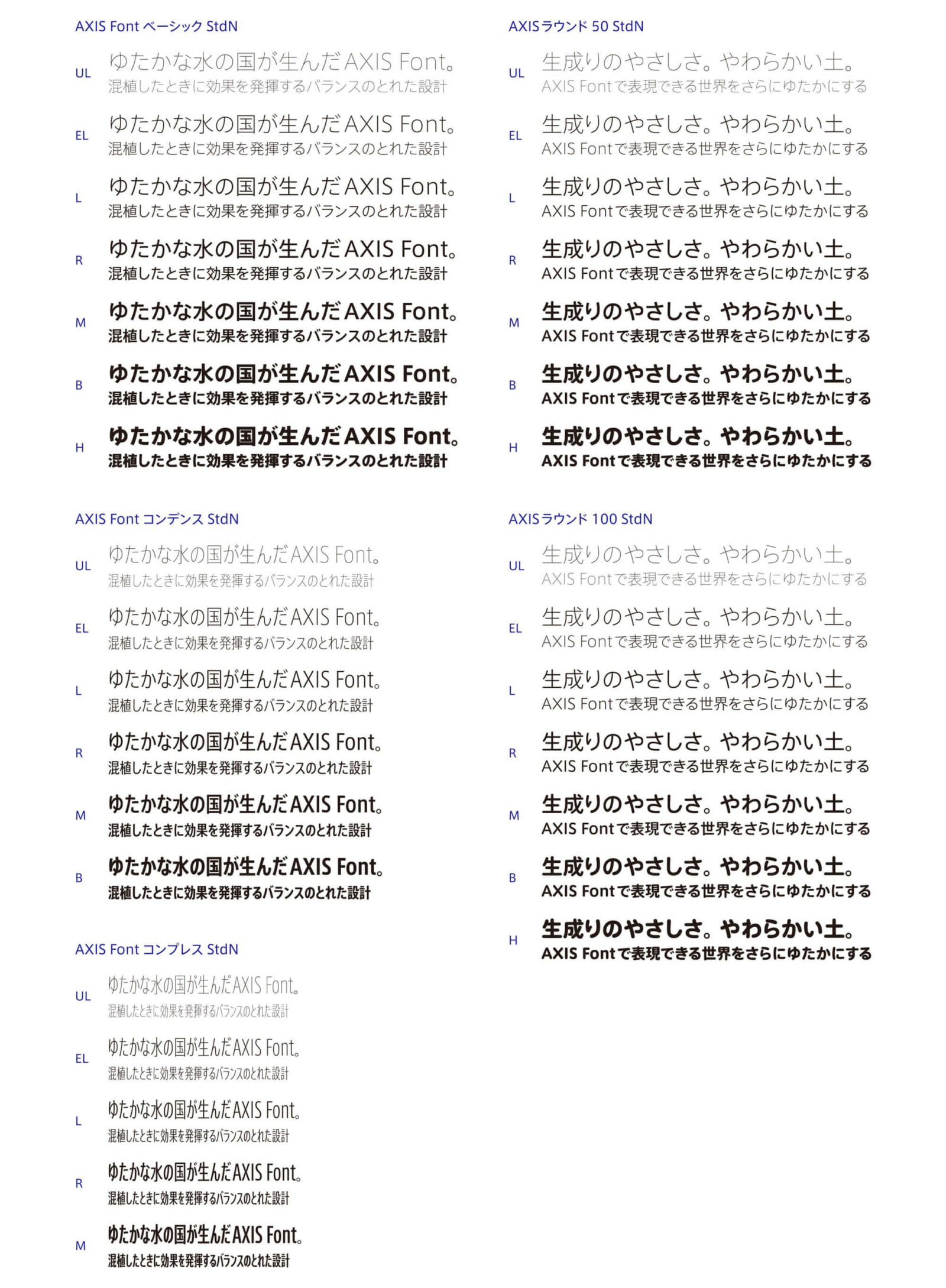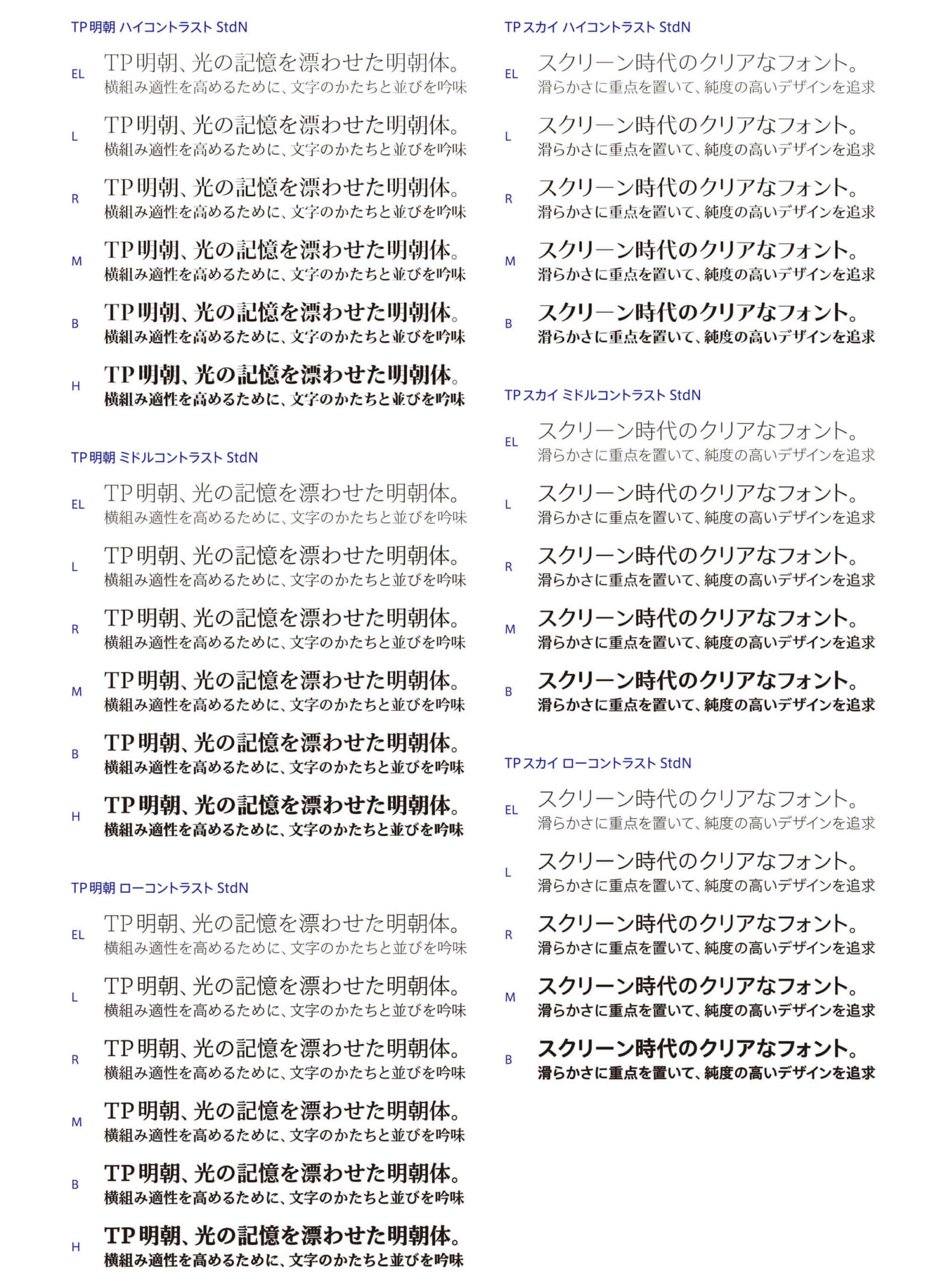
シンプルで風通しのよいデザインが特徴の AXIS Font は、正体のベーシックが 7 ウエイト、長体のコンデンスが6ウエイト、および超長体のコンプレスの5ウエイトからなるバリエーションで、多彩な表現が可能です。AXIS Fontファミリーは、スターバックスやPOLA、としまエコミューゼタウンなどの企業で使用されています。
AXISラウンドは通常の丸ゴシックとは異なり、内径を丸めていないことにより、モダン・サンセリフのシャープな表情を残しています。AXISラウンド50はシャープな輪郭がわずかな丸みを帯び、AXISラウンド100はストロークの先端がほぼ半円の設計になっています。それぞれ7種類のウエイトは、AXIS Fontベーシックの各ウエイトに対応しています。
TP明朝は、横画と縦画の太さの比率を自由に変えられるコントラストという概念を導入しています。シャープで理知的なハイコントラスト、タフで力強いローコントラスト、そして汎用性の高いミドルコントラスト。各コントラストに6つのウエイトを揃えました。TP明朝は、ブリヂストン美術館の図録や、アニメ「アルドノア・ゼロ」で使用されています。
サンセリフ体に「抑揚」の軸を導入した TP スカイは、スクリーンで効果を発揮するよう設計されたフォントファミリーです。アウトラインの滑らかさに重点を置き、アンカーポイントの最小化をはかることで、描画速度における優位性を実現しました。判読性の向上に有用な3つのコントラスト (ハイ、ミドル、ロー)を備え、それぞれ5つのウエイトを備えています。